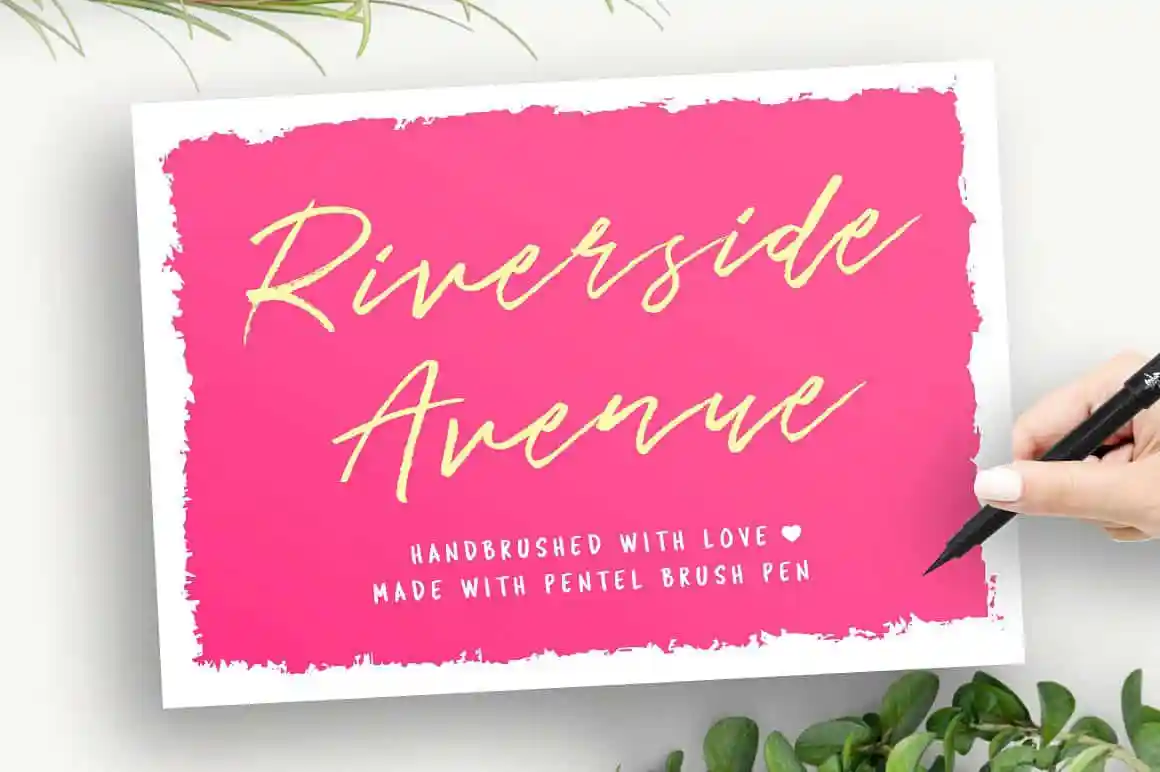
Riverside Avenue Script Font – Download Grátis
Descubra a arte encantadora do Riverside Avenue Script Font, cuidadosamente desenhada com paixão por um artista digital brasileiro chamado 178-MC. Esta fonte brush foi criada usando uma caneta pentel, trazendo à vida texturas únicas e formas elegantes que remetem à escrita manual autêntica. Ideal para diversos projetos como invitações de casamento, logotipos para sites, posts em redes sociais e muito mais. O designer Mats-Peter Forss compartilhou seu trabalho genuíno, oferecendo alternativas para as letras minúsculas que conferem um aspecto fresco e real da escrita manual. Este pacote é perfeito tanto para designers profissionais quanto para entusiastas de gráfica, buscando imprimir uma atmosfera encantadora em seus projetos. Experimente o Riverside Avenue Script Font e deixe sua marca com autenticidade e estilo.